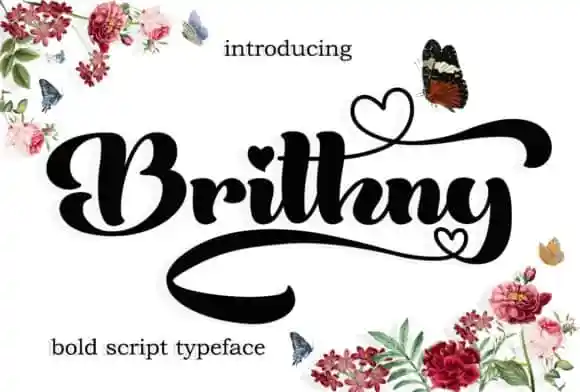
Brithny Script Font – Download Grátis
A Brithny Script Font é uma fonte script que oferece diversidade tanto na posição do piso quanto nas linhas levemente onduladas e suaves. Suas formas, ou “glyphs”, são belíssimas e os detalhes de acabamento são atraentes. É uma fonte script moderna com um tom elegante e atrevido. Brithny é ideal para uso em design gráfico que valoriza estilo e elegância. Com alternativas e fios suaves, essa fonte tem tudo o que você precisa para destacar seu projeto de design. Sealoung fabricou esta linda fonte, um verdadeiro gênio do design gráfico. Não hesite em explorar suas possibilidades para tornar seus projetos mais memoráveis e profissionais.